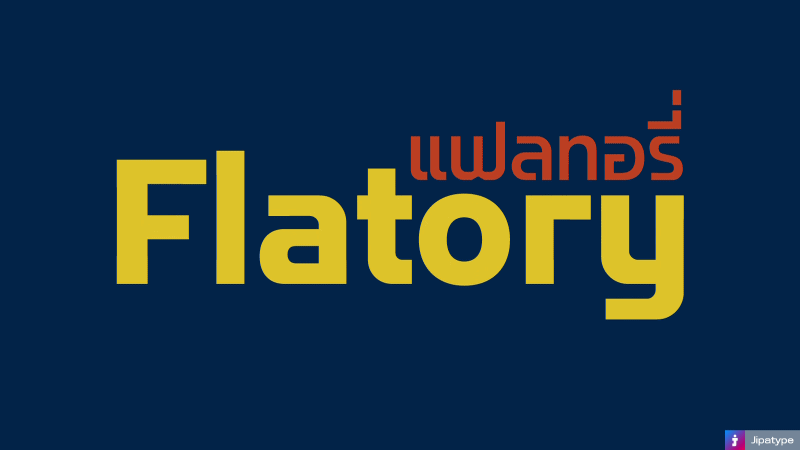
แฟลทอรี่ (Flatory)
คือฟอนต์ที่มีฐานและหลังคาของตัวอักษรที่แบนราบไปกับเส้นแนวนอนให้ความรู้สึกมั่นคงแข็งแรงไม่หวั่นไหว เพื่อให้ธุรกิจอุตสาหกรรมเดินหน้าอย่างมั่นคง ต่อทุกสภาพเศรษฐกิจ
ออกแบบโดย : อานุภาพ ใจชำนาญ
- น้ำหนัก Regular
- มีเฉพาะอักษรไทยเท่านั้น